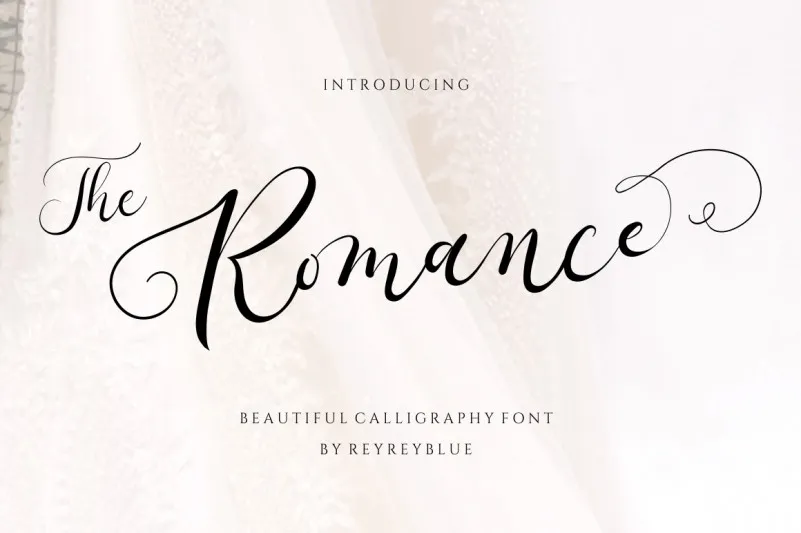
The Romance Font – Fonte Grátis
The Romance Font
A fonte The Romance Font é perfeita para aqueles que procuram algo sofisticado e elegante para seus projetos de design. Seu estilo delicado e fluido, transmitindo uma sensação única e um impacto poderoso, adicionará um toque luxuoso a qualquer projeto que você desejare criar. Esta fonte é PUA encoded, o que significa que você pode facilmente acessar todos os encantadores caracteres e ligaturas disponíveis. Ideal para aplicativos de arte gráfica, editoriais de livros ou criação de logotipos de marcas em estilos modernos, The Romance Font traz um toque autêntico ao seu trabalho. Seja você designer gráfico, ilustrador ou qualquer outro profissional que valoriza a qualidade e o design, essa fonte será uma ótima escolha para enriquecer os seus projetos de forma elegante e sofisticada.